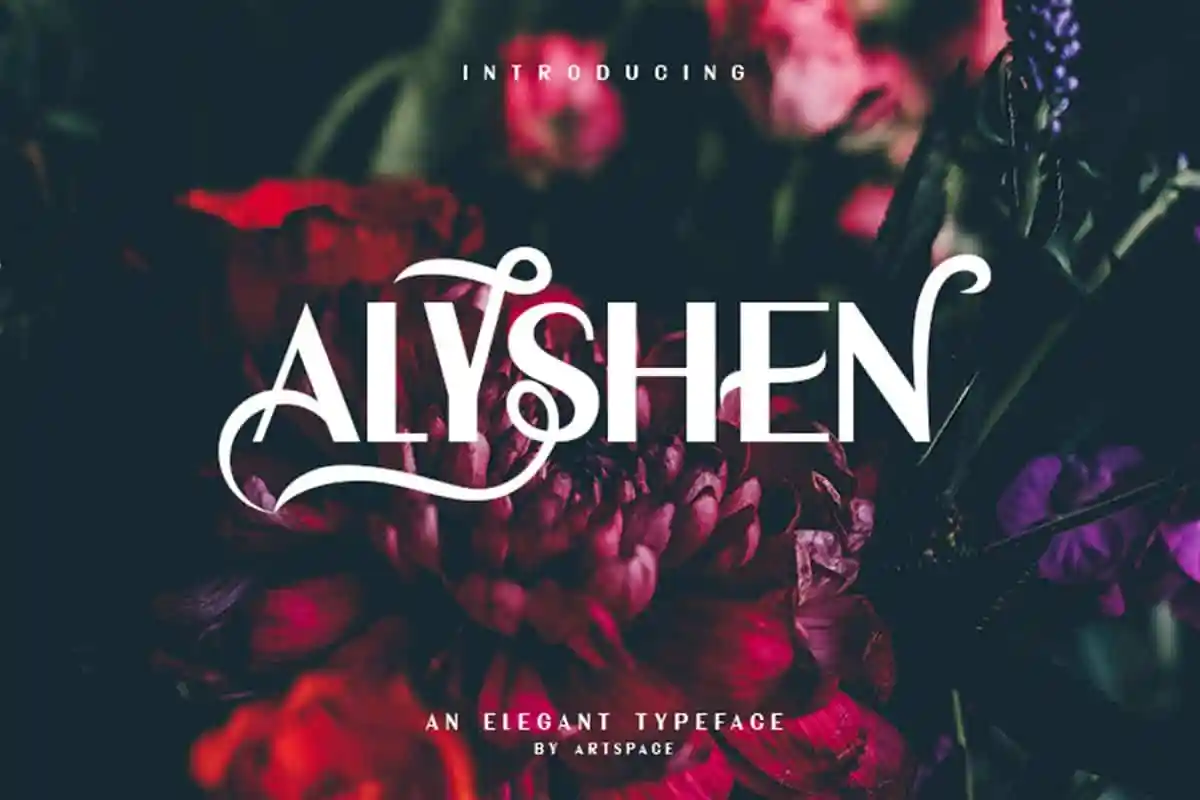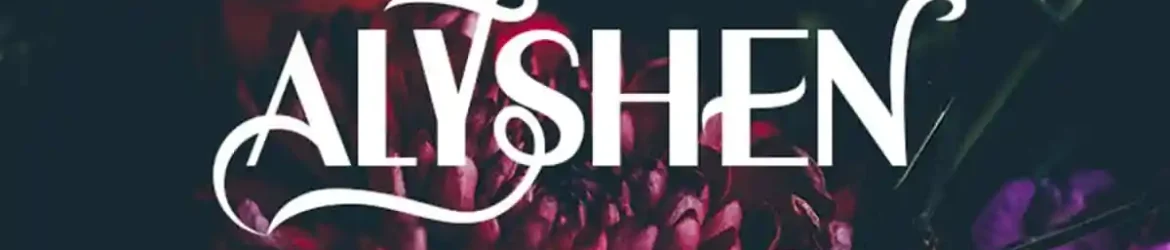
ALYSHEN Typeface – Download Grátis
Alyshen Typeface é uma elegante fonte de tipo gêmeo que se destaca pela sua simplicidade e criatividade. Essa fonte sans-serif tem estilos delicados, oferecendo alternativas para várias letras, tornando-a perfeita tanto para criações de logotipos quanto para projetos de panfletos e marcas, além de design de camisetas. Embora seja limitada em alguns usos específicos, Alyshen se destaca como uma opção ideal para a criação de trabalhos criativos que precisam de um charme único e não tão convencional quanto algumas fontes tradicionais. Uma ótima escolha para designers buscando algo novo e intrigante para seus projetos visuais. Esta fonte foi criada pelo designer 24Design, conhecido por suas criações atraentes e personalizadas que sempre procuram surpreender o público de maneira inovadora. Com um design limpo e minimalista, Alyshen é uma excelente adição para qualquer designer que busca criar algo realmente único em seus trabalhos visuais.